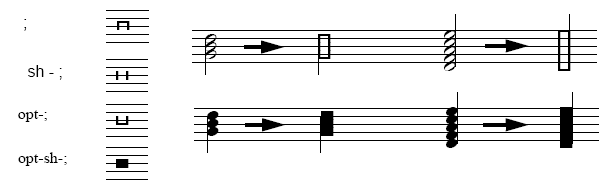
Queste teste di note vi consentono di notare agevolmente i cluster sia indeterminati che determinati. Dopo aver inserito le note con le usuali modalità, usate lo Strumento Speciale per cambiare le teste delle note. Questi caratteri sono disponibili soltanto con i font Engraver Font Set e Engraver Font Extras.
Indeterminati
Determinati